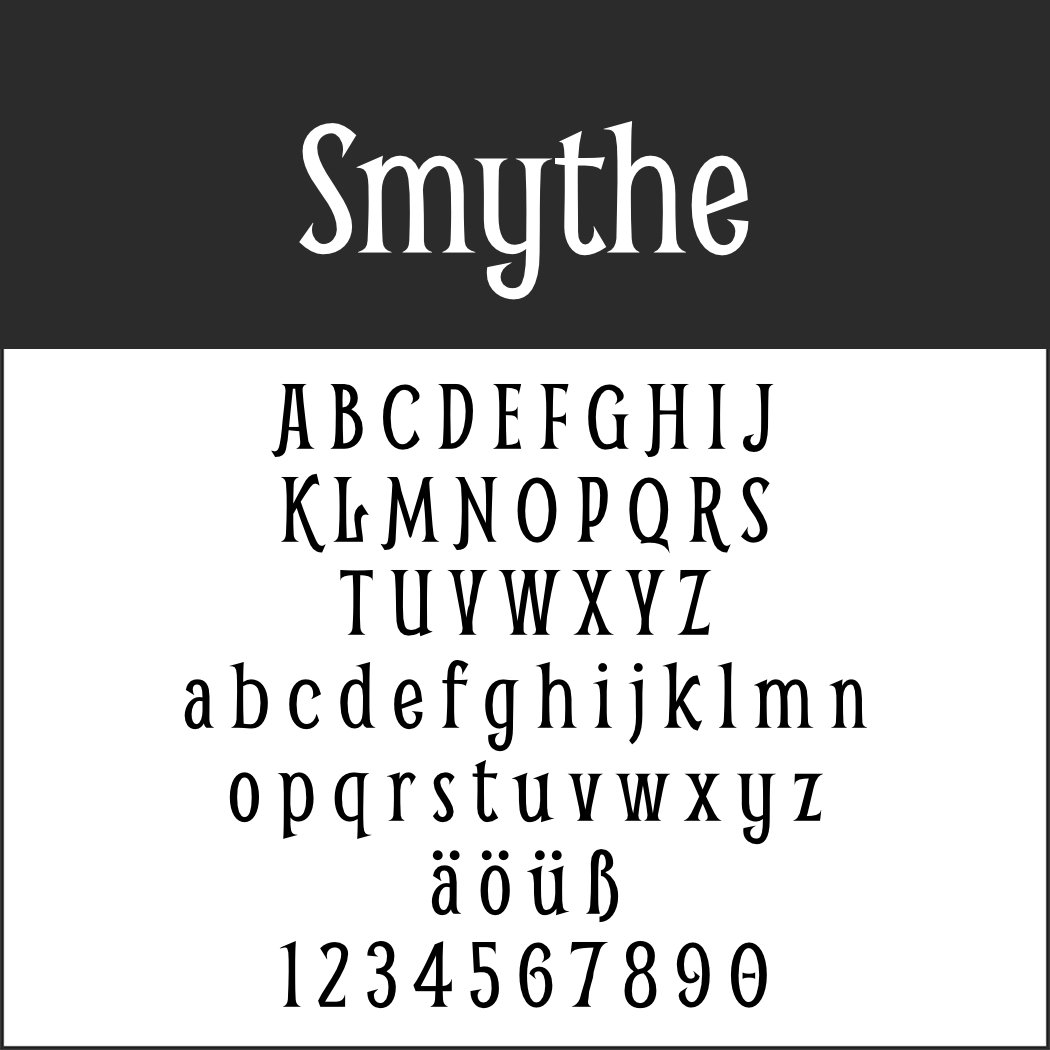
Ihren Namen bekam die Epoche erst, als sie schon lange der Vergangenheit angehörte: in den 1960er Jahren. „Art déco“, die dekorative Kunst, steht für eine Stilrichtung, die sich nach dem Ersten Weltkrieg auf Architektur, Möbel und Dinge des täglichen Bedarfs ausdehnte.
Entstanden aus dem Jugendstil (Art nouveau) erzählt der Art déco vom Optimismus der Menschen (hauptsächlich denen aus der Oberschicht) sowie dem Glauben an neue technische und gesellschaftliche Errungenschaften. Die Art déco Schriftart vermittelt eben dieses Gefühl und verfehlt auch heute noch ihre Wirkung nicht.
Art déco Schriftart: Beauty School Dropout
Inspiriert von einer Leuchtreklame im Art-déco-Stil entwickelte der Designer diesen Font, der durch seine langen Oberlängen Aufmerksamkeit garantiert.
Art déco Schriftart: Calamity Jane NF
Wie die Namensgeberin, die legendäre Wildwest-Heldin Calamity Jane, gibt sich dieser Font unangepasst. Die Großbuchstaben stammen von einem Plakat des Théâtre Moderne in Paris aus den 1930er Jahren, die Kleinbuchstaben von der Schrift Amsterdam um 1900. Das Ergebnis wirkt trotz seiner Eigenwilligkeit elegant.
Art déco Schriftart: Coventry Garden
Art déco und Jugendstil geben sich hier ein Rendezvous, passend für alles, das die Stimmung der Belle Epoque erzeugen soll.
Art déco Schriftart: Dubba Dubba NF
Unbedingt ein Hingucker: die ausgeprägten und unkonventionellen Oberlängen dieser Schriftart. Als Vorlage diente das Logo von Warner Brothers.
Art déco Schriftart: Hilo-Deco
Nüchtern und dennoch beschwingt wirkt der Font, der vom ersten Blick an eindeutigen Art-déco-Charme verströmt.
• Design: Narrowhouse
Art déco Schriftart: Ironick NF
Art déco à la française: Der Font wurde der Schrift einer alten Werbung für Gauloises-Zigaretten nachempfunden.
Art déco Schriftart: Kilsonburg
Das Spiel mit unterschiedlichen Schriftstärken beeindruckt durch seine Eleganz. Die kommt nicht von ungefähr, denn als Vorlage diente ein Vogue-Titelblatt aus dem frühen 20. Jahrhundert.
1920er Font: Korner Deli NF
Ein verwittertes Blechschild von Scialo Brothers Bakery in New York inspirierte den Designer zu diesem Font mit teilweise recht eigenwilligen Buchstabenformen.
1920er Font: Madison Square NF
Ein großer Name für einen Font, der an glanzvolle Entertainment-Zeiten erinnert und einen ausgeprägten Art-déco-Charakter besitzt.
1920er Font: ReynoldReynold
Art déco Schriftart mit starkem Jugendstil-Verweis: Dieser Font erinnert an Blechschilder aus der Anfangszeit der Reklame. Deshalb eignet sich Reynold vor allem, wenn man genau diesen Effekt erzielen möchte.
1920er Font: SmytheSmythe
Der britische Designer bediente sich für Smythe verschiedener Schriftarten um die vorletzte Jahrhundertwende. Und so kann der Font auch für die unterschiedlichsten Gelegenheiten rund um Nostalgisches zum Einsatz kommen.
• Design: Vernon Adams